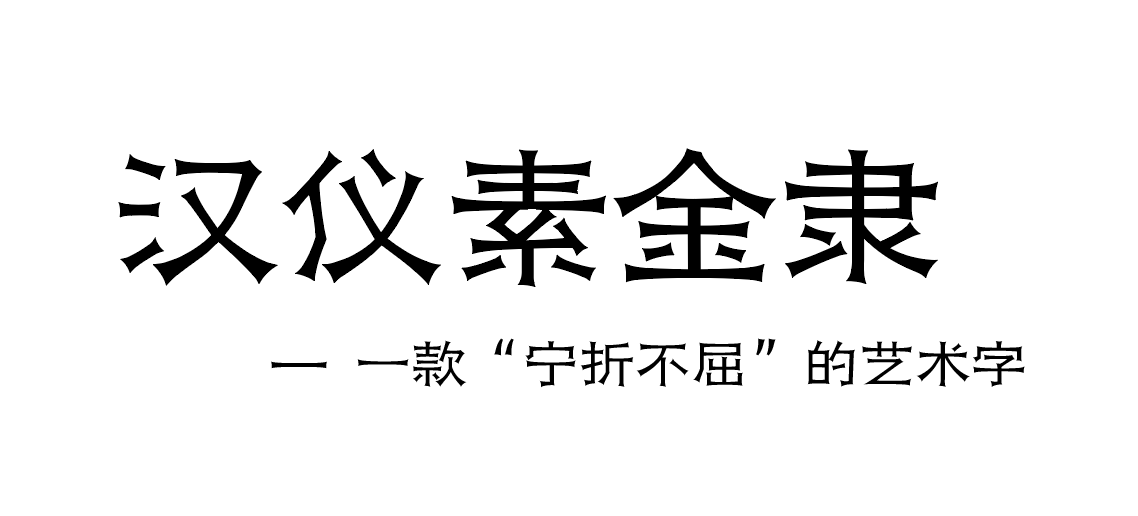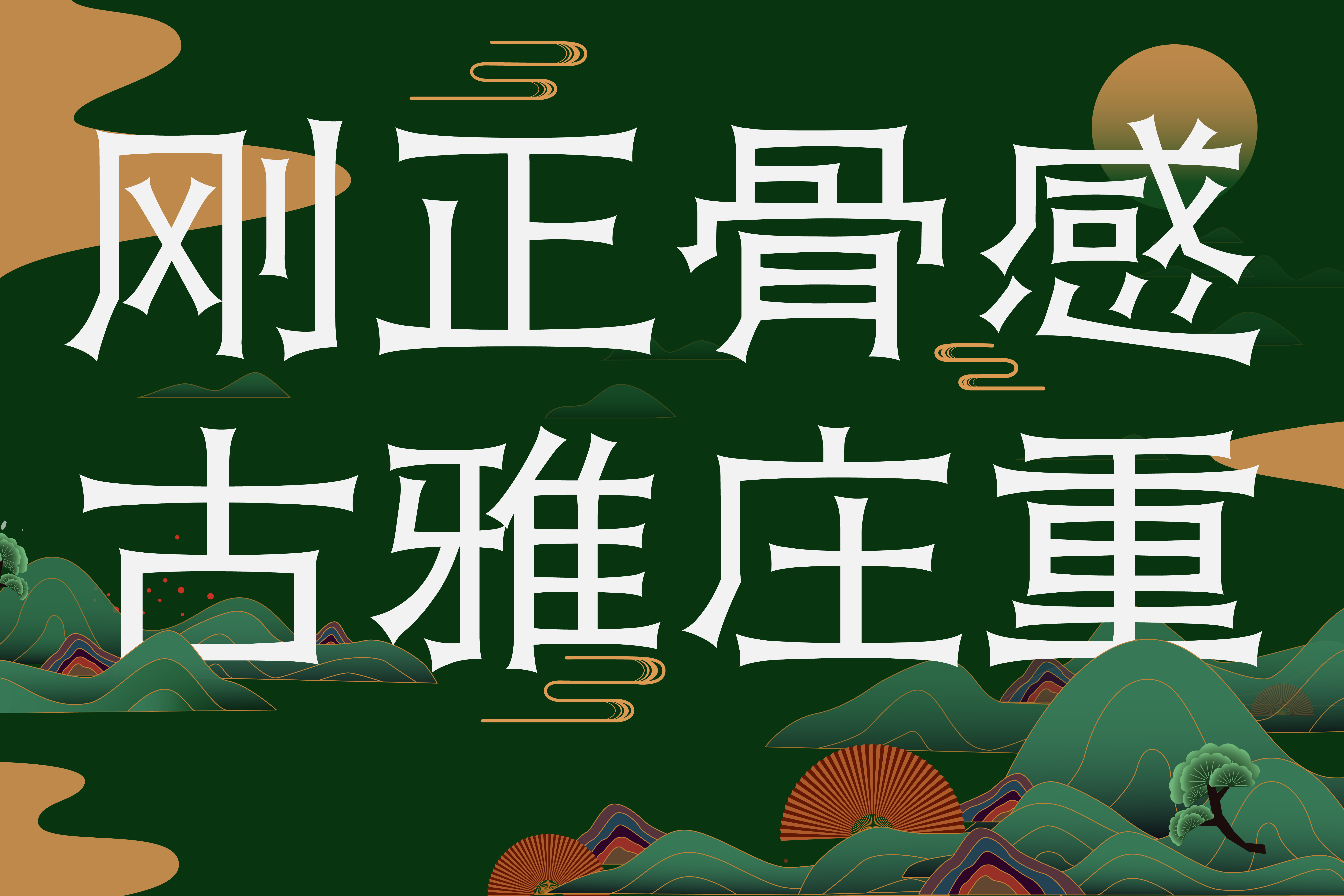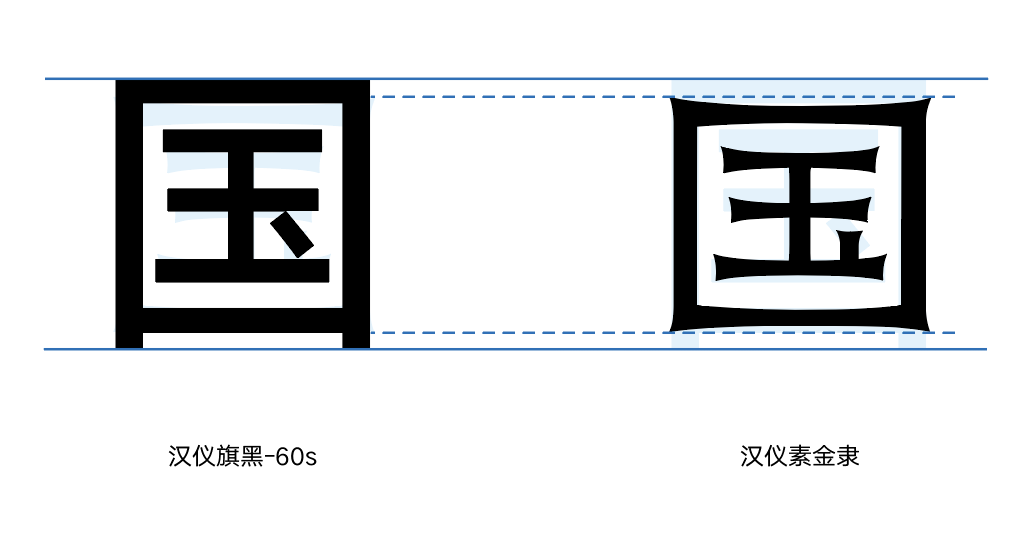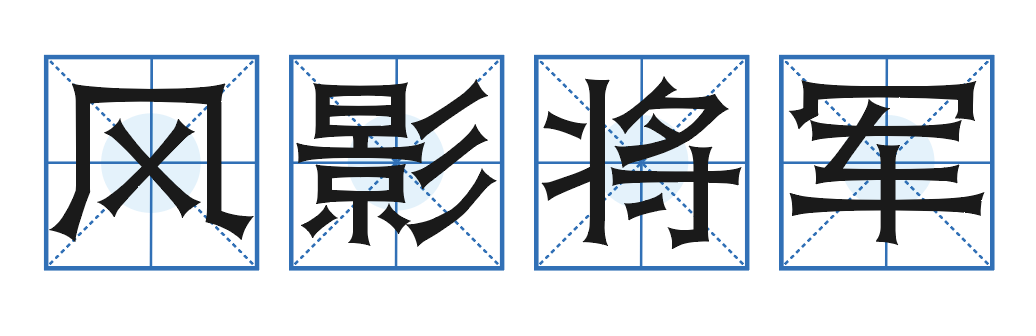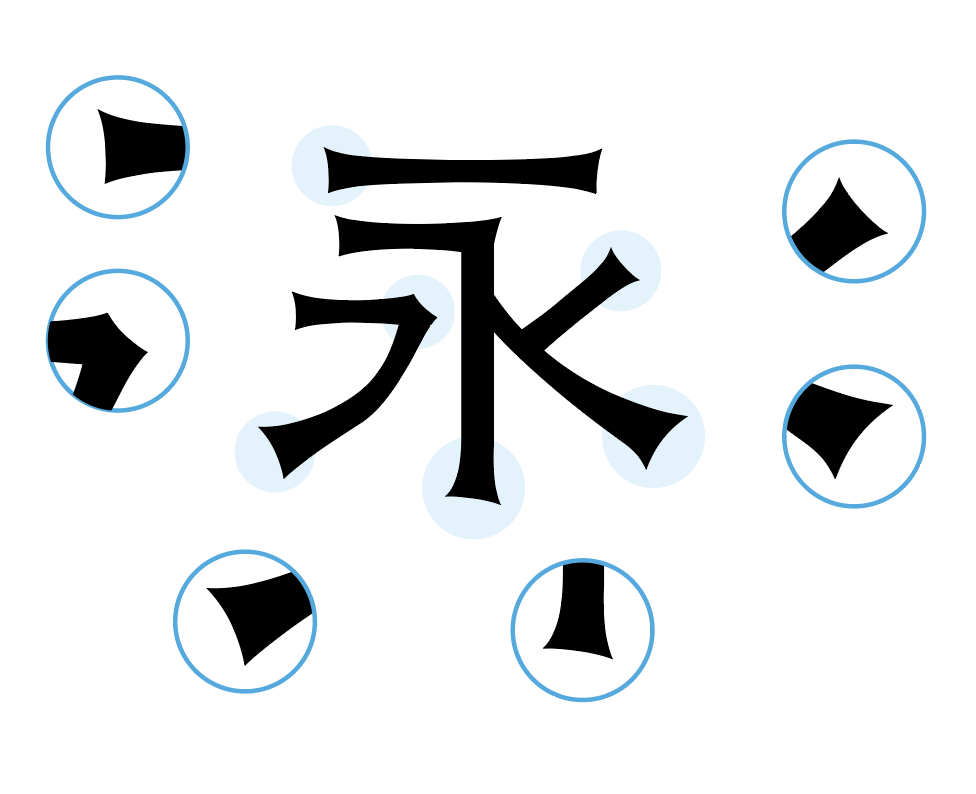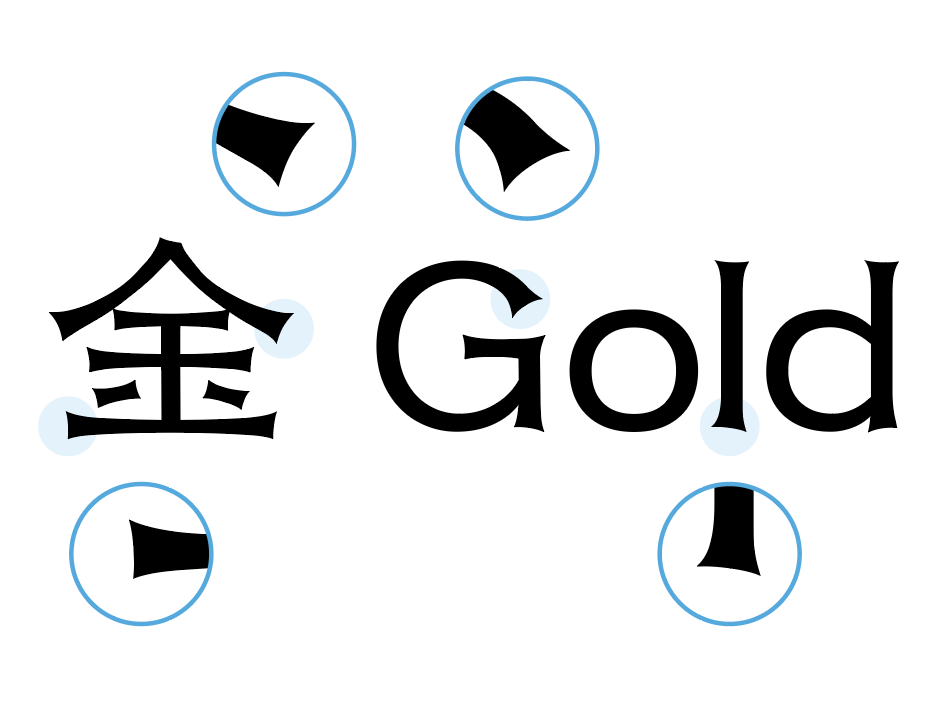
汉仪素金隶字体介绍,一款刚正骨感的字体
整体特点
“汉仪素金隶” 是一款刚正骨感的字体。设计师采用了隶书的形体结构,将隶书“蚕头雁尾”这一特征降到最低,做成了夸张的“喇叭口”装饰。这款字体风格简洁清劲,将传统书法艺术与现代设计形式融合,散发出一种新古典气息,可以作为标题字被应用于游戏、影视、产品包装和杂志封面等多种场景。
字形特点
“汉仪素金隶” 采用了隶书的结构,字形宽扁,横长竖短,给人一种稳重的感觉。
“汉仪素金隶” 的字形结构严谨,字面疏朗宽博,重心平稳一致,给人以均匀、整洁、清新、典雅的整体感。
笔画特点
“汉仪素金隶” 的字体刚劲挺拔。笔画粗细均匀,部分笔画改曲为直,改直为折。一笔一画都如金属般钢硬,有一种“宁折不屈”的态度。
“汉仪素金隶” 的所有笔画两端均做成了不同夸张程度的“喇叭口”装饰。笔画两头粗中间细,犹如弯弓蓄势。
西文字母
“汉仪素金隶” 的西文保留和延用了中文字形的风格特点。恰当的运用了中文的笔画装饰,增强了字母的设计感,同时也具有较强的识别性。
排版效果
案例展示